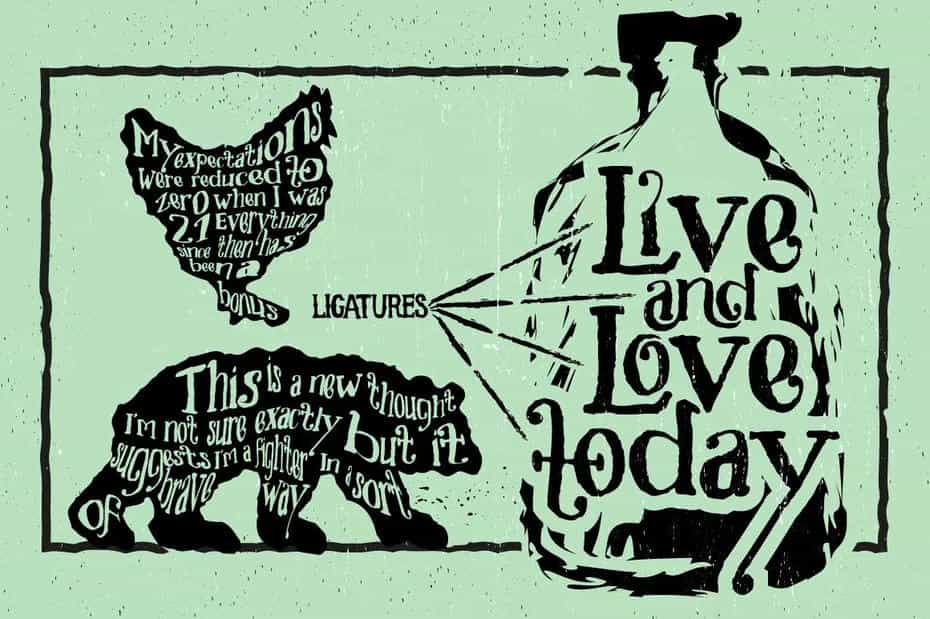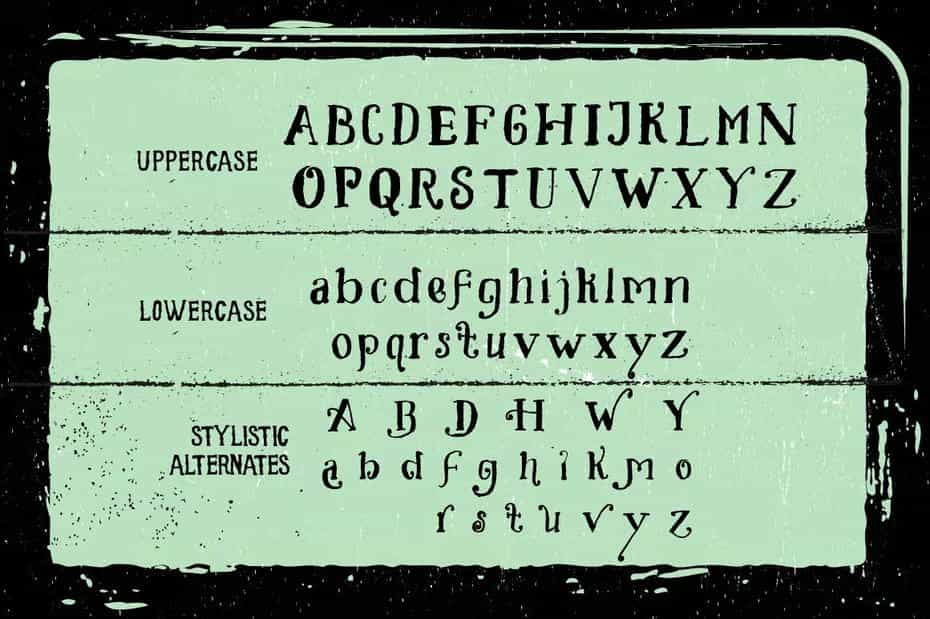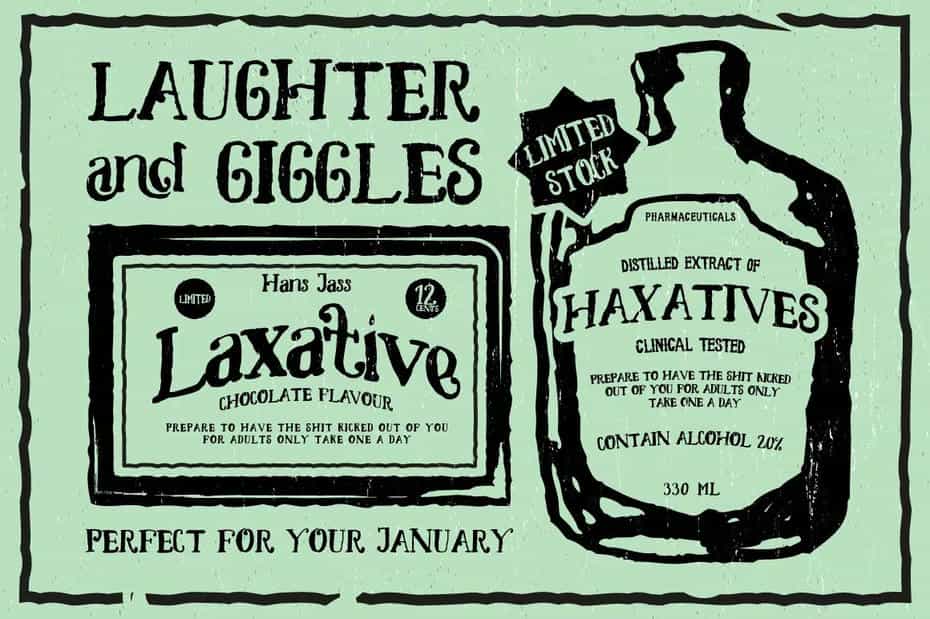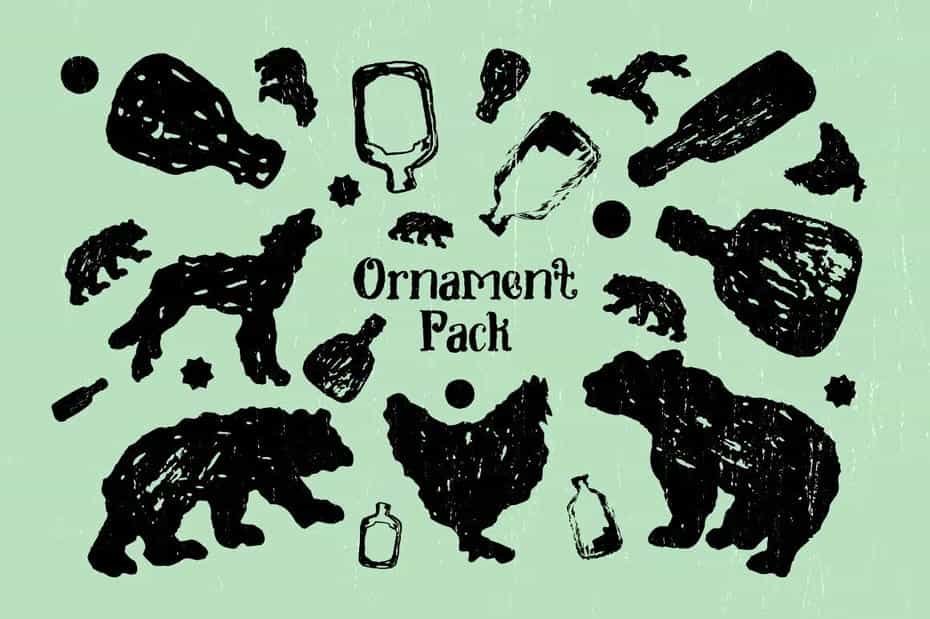
دانلود فونت انگلیسی TOXINE typeface + Ornament pack
فونت انگلیسی TOXINE typeface : این مجموعه شامل یک فونت کلاسیک است که برای برچسب ها، پوستر ها، پروژه های وینتیج، طراحی تی شرت و … مناسب می باشد.
فونت انگلیسی TOXINE typeface + Ornament pack